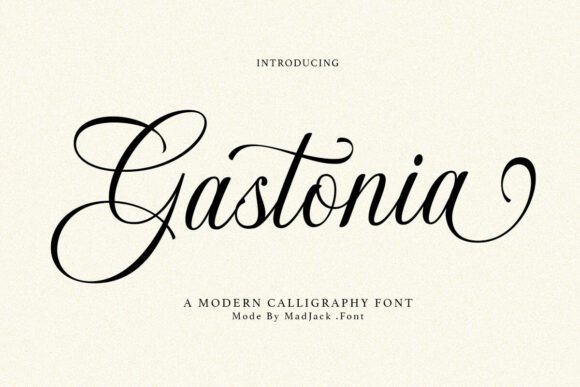
Gastonia Script
Если вы ищете высококачественные ресурсы, такие как Gastonia Script, этот премиум-пакет — фантастический выбор для ваших творческих проектов.
Созданный с высокой точностью, Gastonia Script предоставляет чистые векторы, плавную типографику и коммерческую лицензию для вашего спокойствия.
Создаете ли вы продукты POD (печать по требованию), свадебные приглашения или графику для социальных сетей, Gastonia Script станет идеальным выбором.